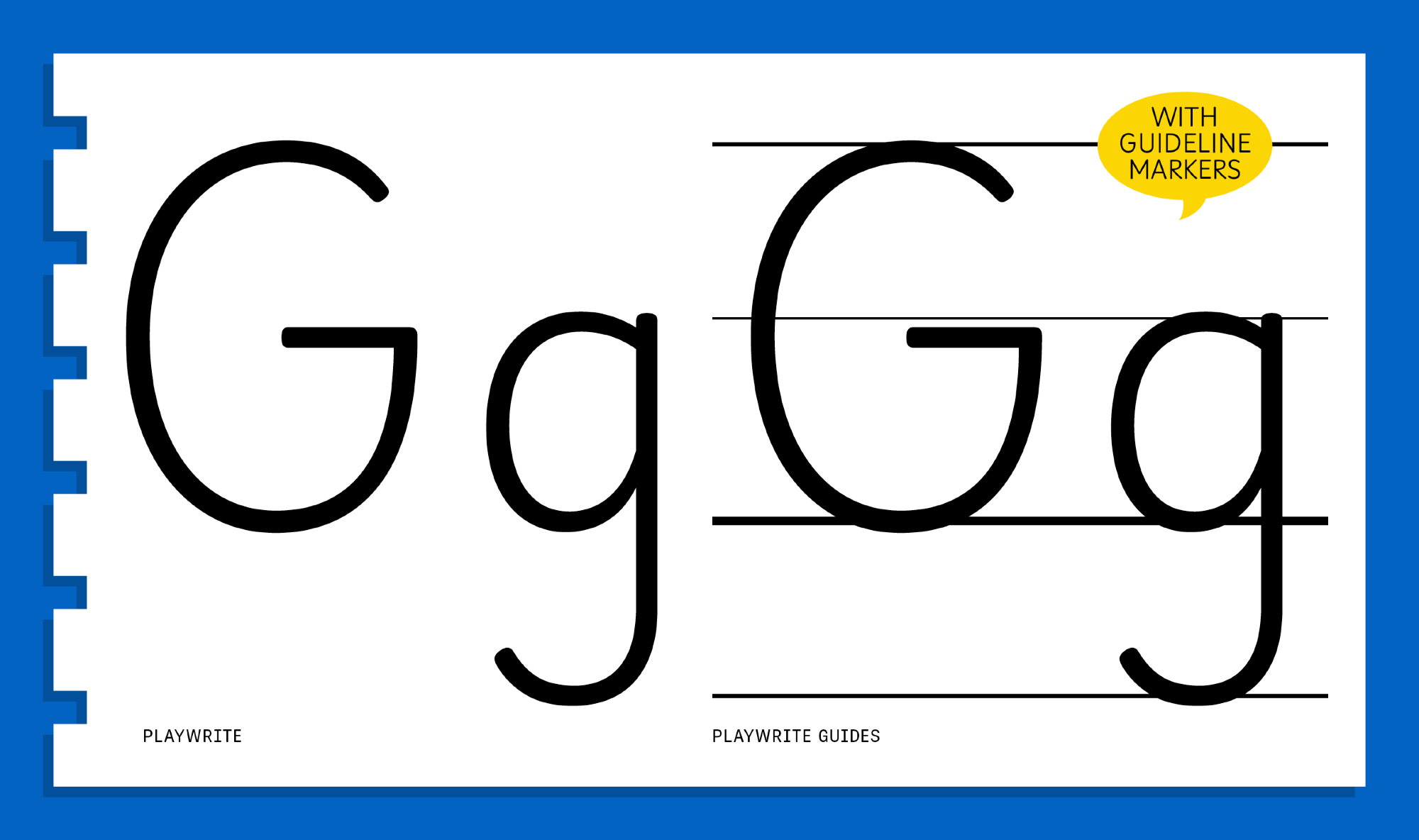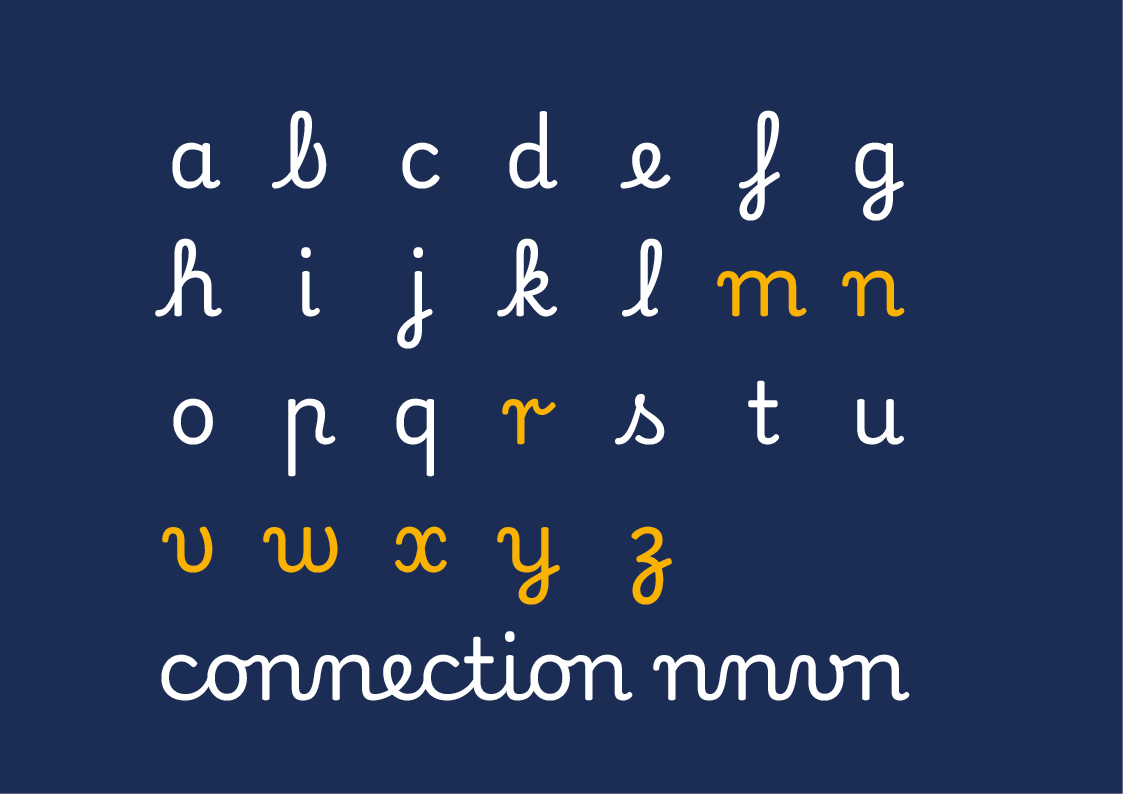
- Antiqua Schreibschrift
Playwrite ist ein kostenlos nutzbares System zur Darstellung von Schulausgangsschriften. Es ist so ausgelegt, dass regionale Varianten von bereits über 40 Ländern generiert werden können. Darüber hinaus können verschiedene Komplexitätsstufen gewählt werden (zum Beispiel freistehend oder verbunden, Druckschrift oder Kursivform, einfach oder mit zusätzlichen Schwüngen dekoriert). Eine Linierung kann ebenfalls zugeschaltet werden.